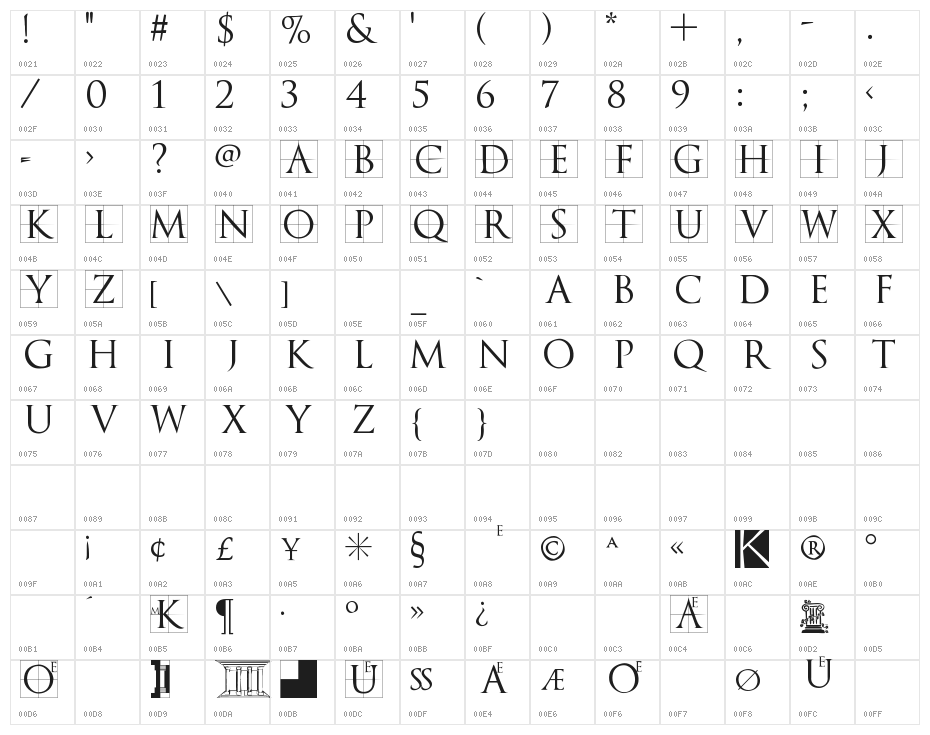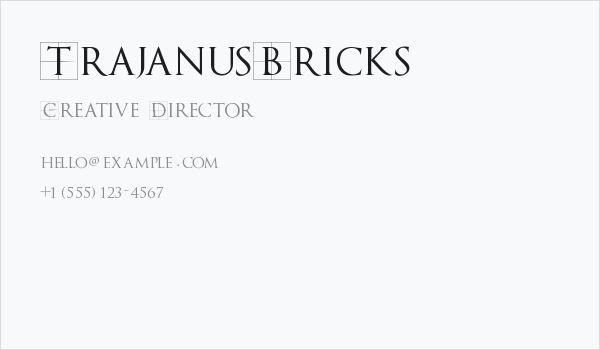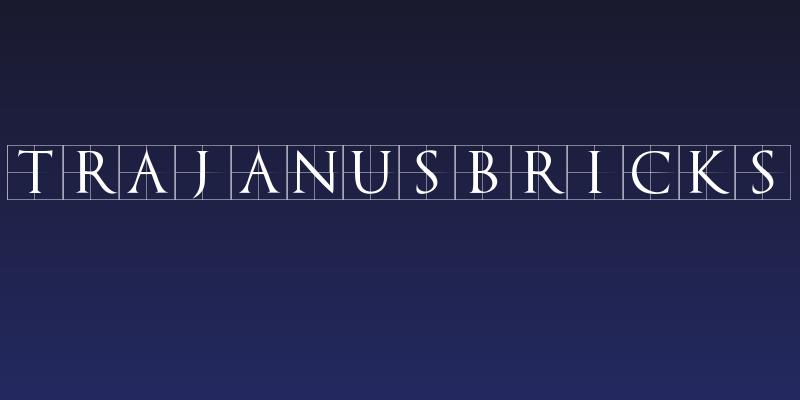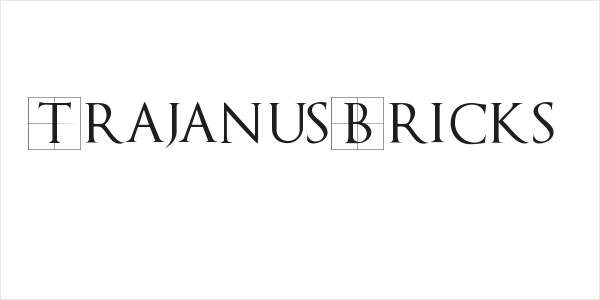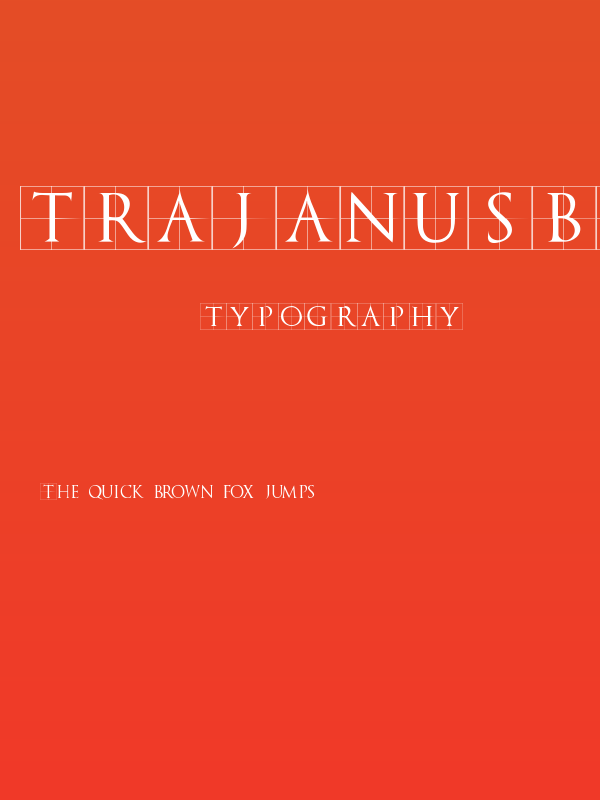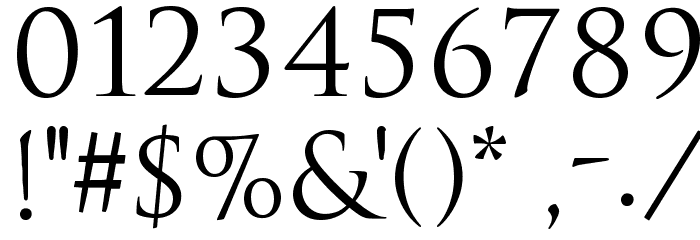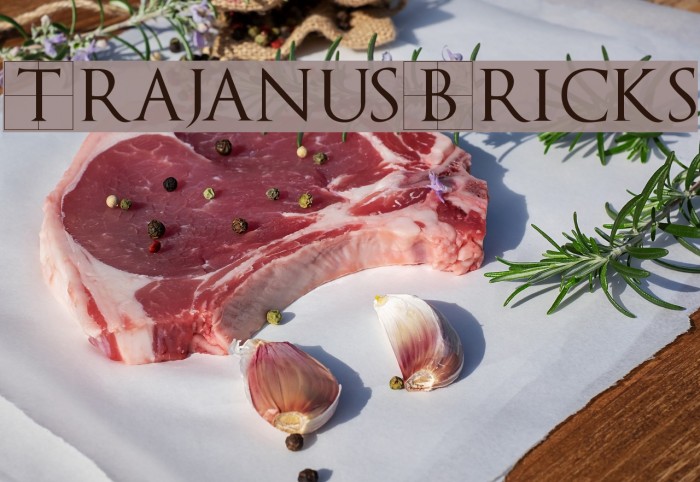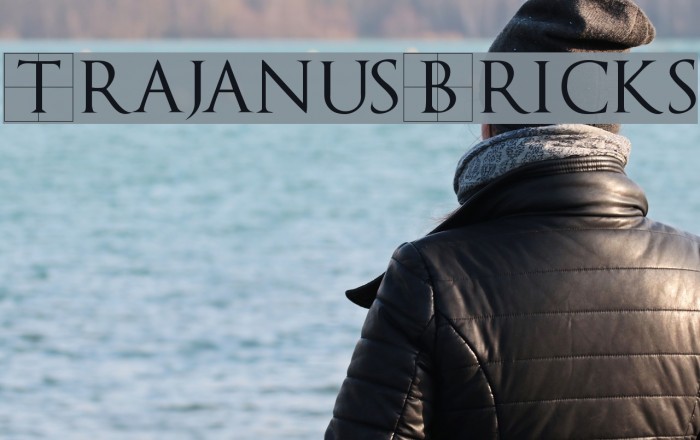
TrajanusBricks Font
Fonts by Manfred Klein - manfred-klein.ina-mar.com
| Estilo general | Classic |
| Caso de uso | Headlines, Body text, Logos |
| Proyectos propuestos | Ideal for projects that require a touch of elegance and tradition, such as book covers, historical documentaries, formal invitations, and branding for luxury products. |